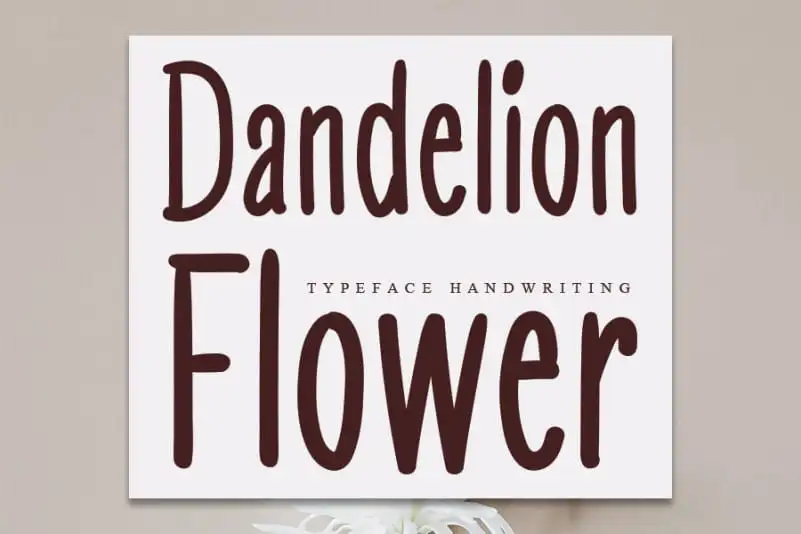
Dandelion Flower Display Font é uma elegante fuçna escrita a mão que traz uma sensação de sofisticação. Seja você criando cartões de agradecimento para suas convidadas, cartas de casamento, cartazes com citações ou até mesmo um logotipo para sua empresa, essa fonte oferece um toque refinado e autêntico que trará sua design à vida. A Dandelion Flower Display Font é perfeita para qualquer projeto que busque transmitir uma mensagem única de forma elegante e memorável. Seja você um artista digital ou designer gráfico, essa fonte irá adicionar valor a seu trabalho.